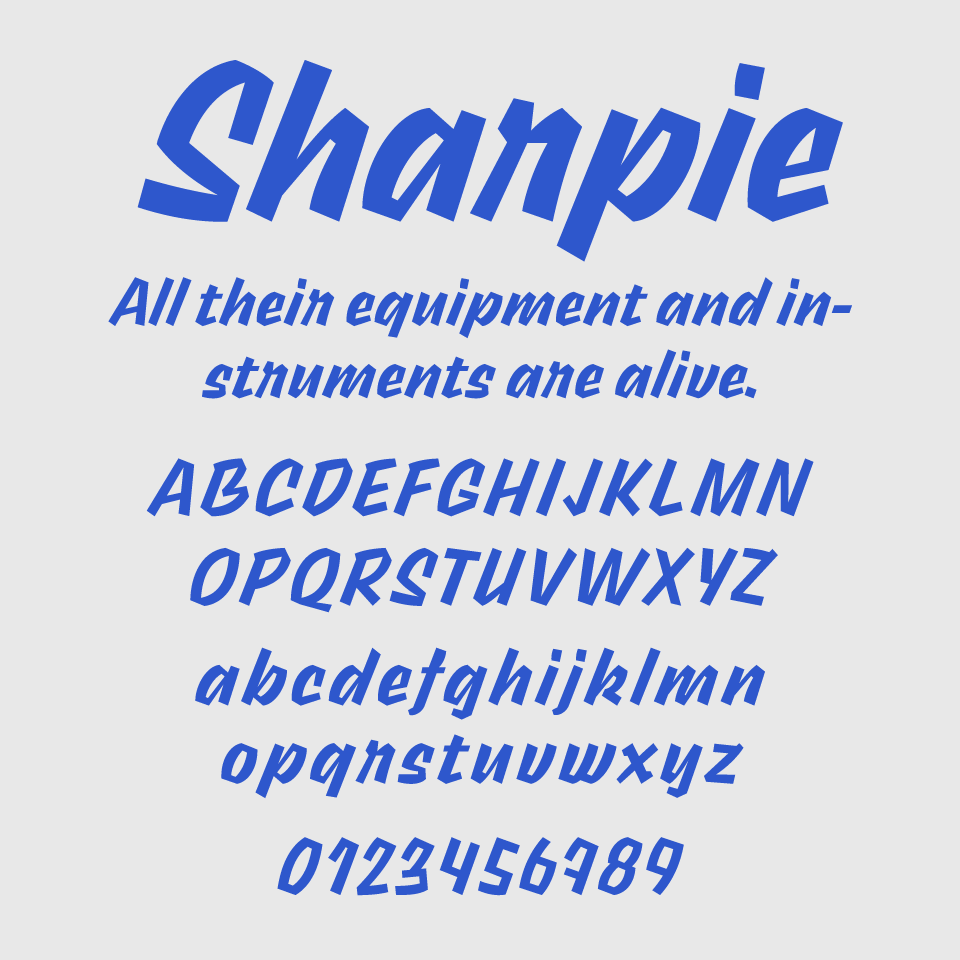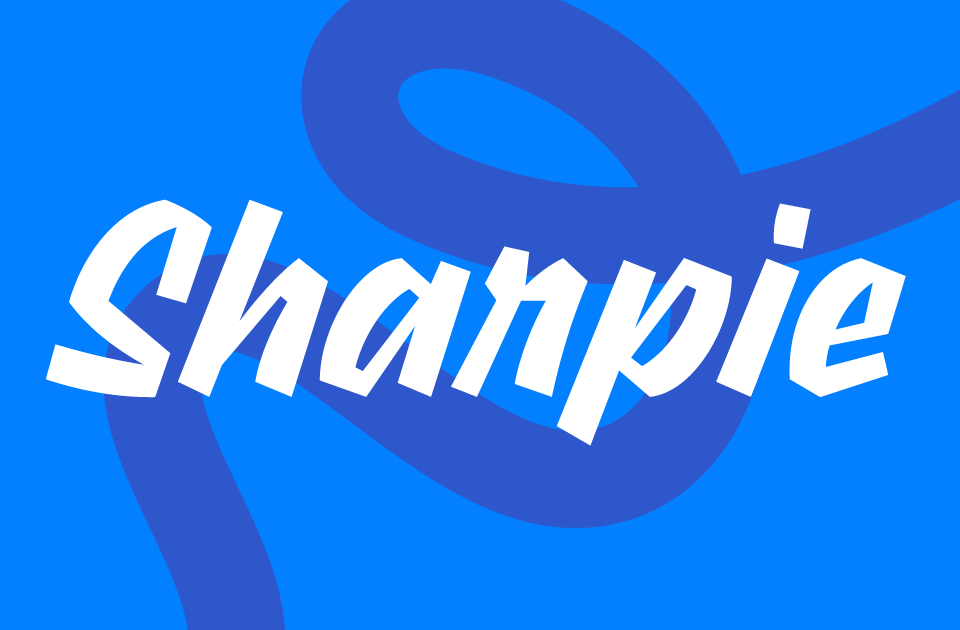
Sharpieフォントは、マーカーペンで勢いよく書き殴ったような活き活きとしたエネルギーが魅力の手書き風フォントです。筆致の角度や太さの変化がラフで、どこかストリートアートやグラフィティのような空気感を持っているフォントです。
右上がりの傾斜や跳ねるような文字の配置から、勢いのあるセリフやユーモラスな表現にぴったりです。キャッチコピーやタイトル、ポスターなど「一言で惹きつけたい」シーンで強力なアクセントとしてもぴったりな、元気とクセが共存したフォントです。